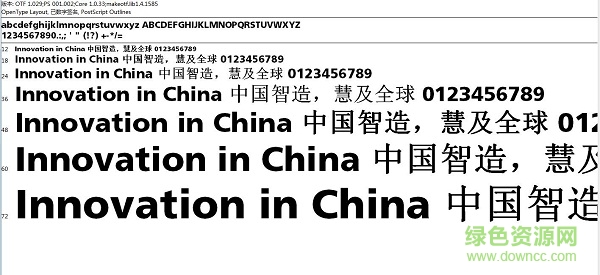
frutiger lt std 55 roman字體
frutigerltstd系列字體包含了frutigerltstd roman、frutigerltstd bold、frutigerltstd-black、frutigerltstd-light以及frutigerltstd-cn等多款勻稱漂亮的無襯線字體,歡迎免費下載!
襯線字體適用領(lǐng)域
1.無襯線體給人的感覺是時尚簡約,優(yōu)雅端莊。常用于高端品牌或發(fā)布會現(xiàn)場等。
2.同時無襯線的黑體給人一種干凈,簡約的感覺,同時還帶著輕松休閑的氣氛。
frutigerltstd roman字體